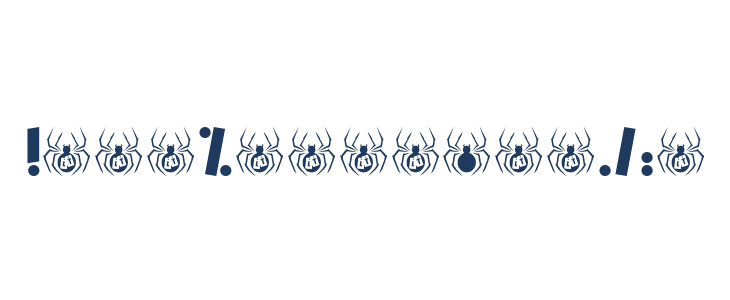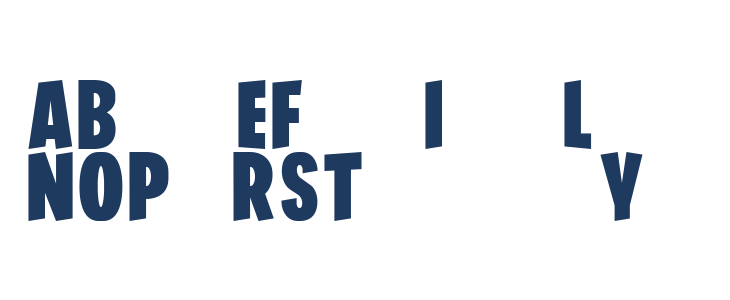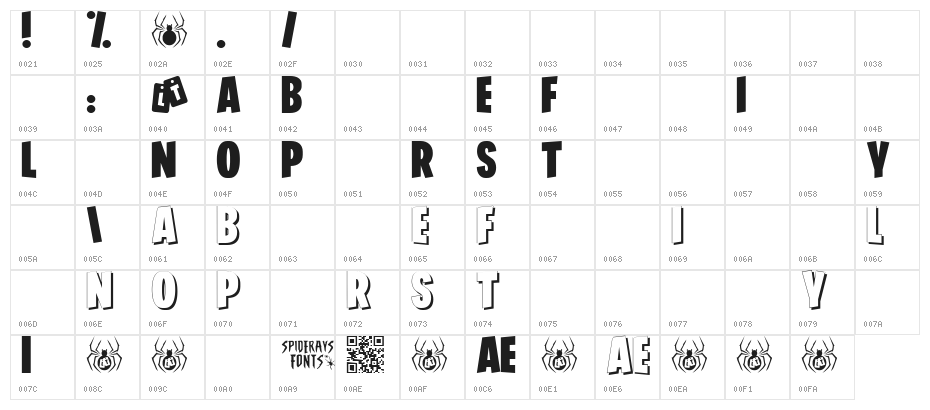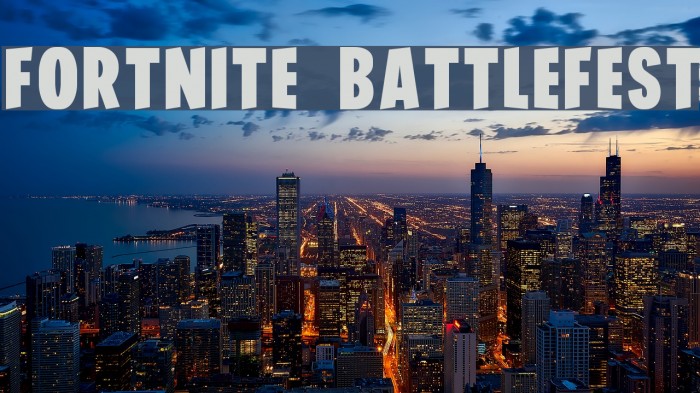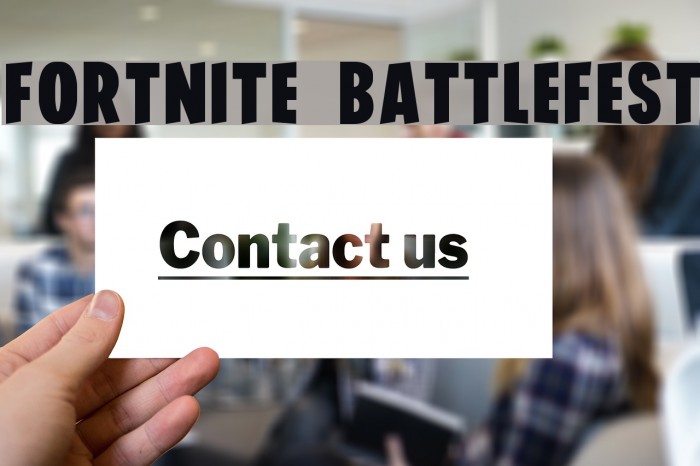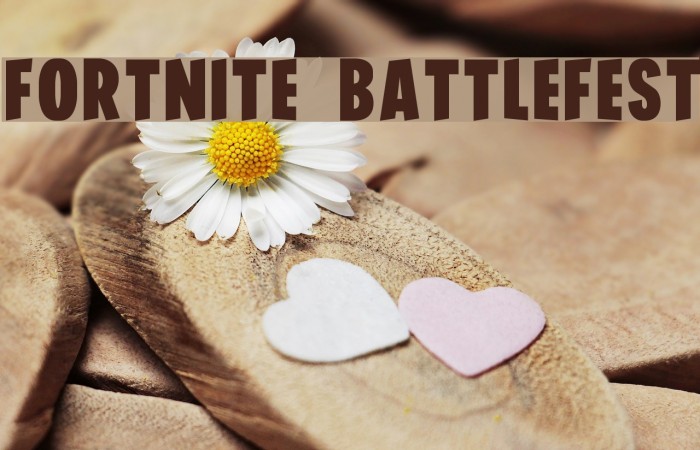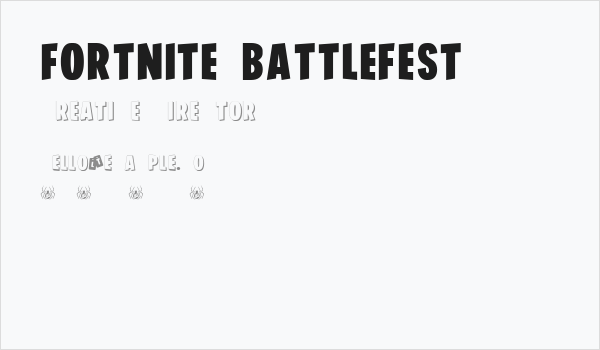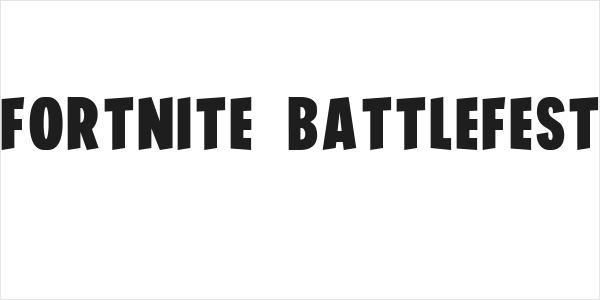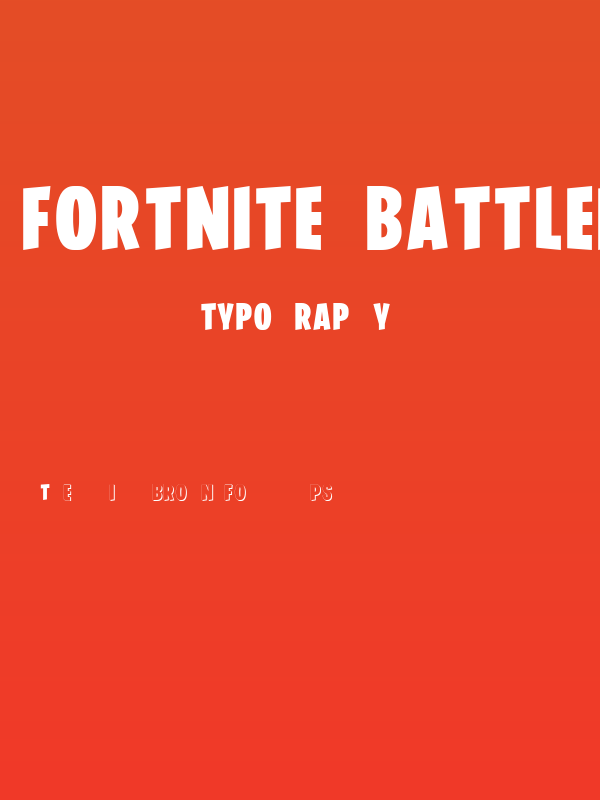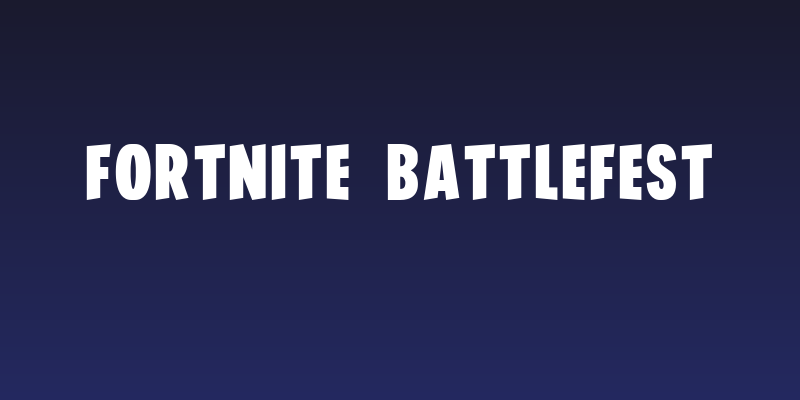
FORTNITE BATTLEFEST Font
FORTNITE BATTLEFEST
| समग्र शैली | Playful, Dynamic, Bold |
| उपयोग का मामला | Headlines, Logos, Posters |
| सुझाए गए प्रोजेक्ट | Ideal for video game titles, comic book covers, posters, and any project needing a bold, eye-catching typeface. |